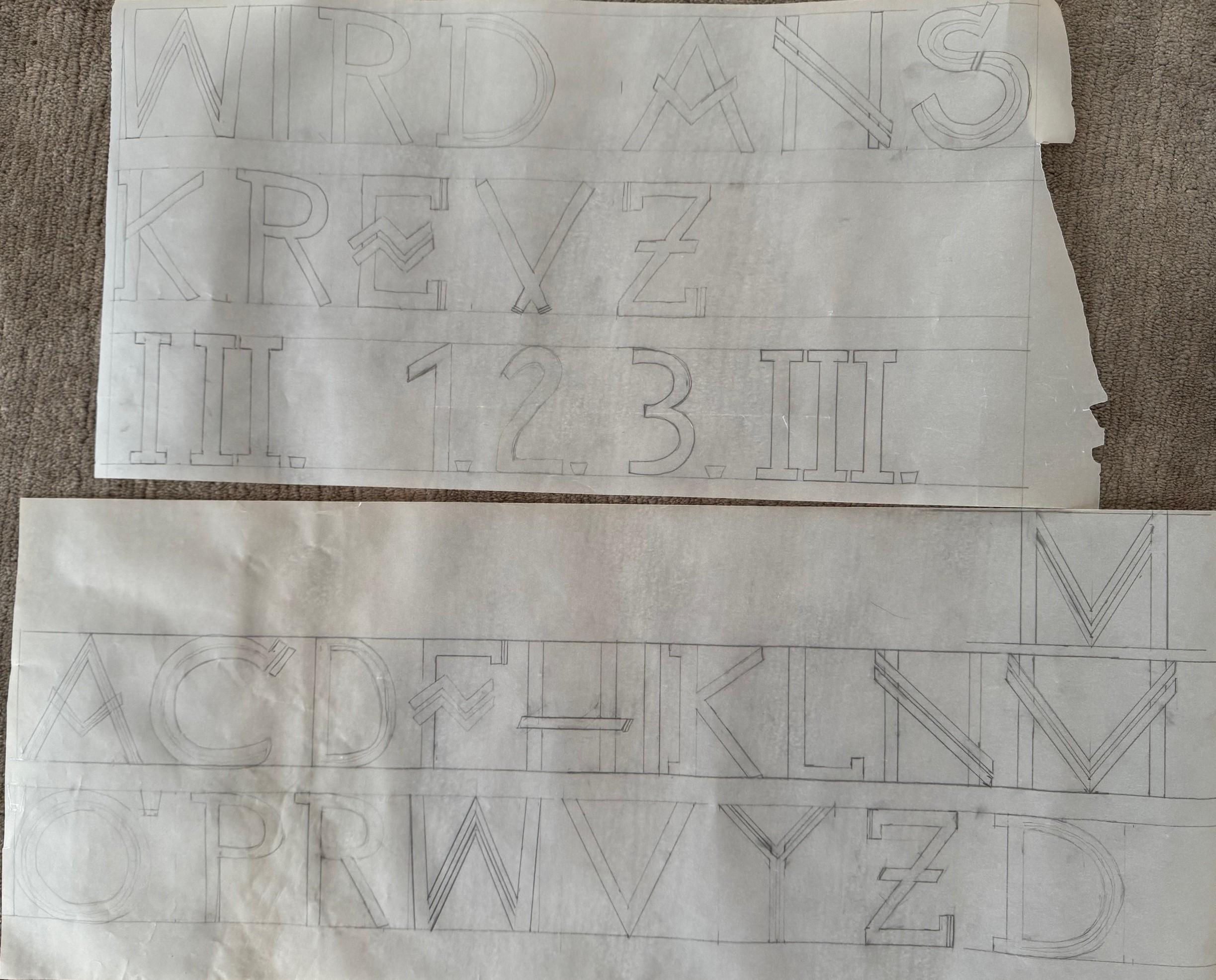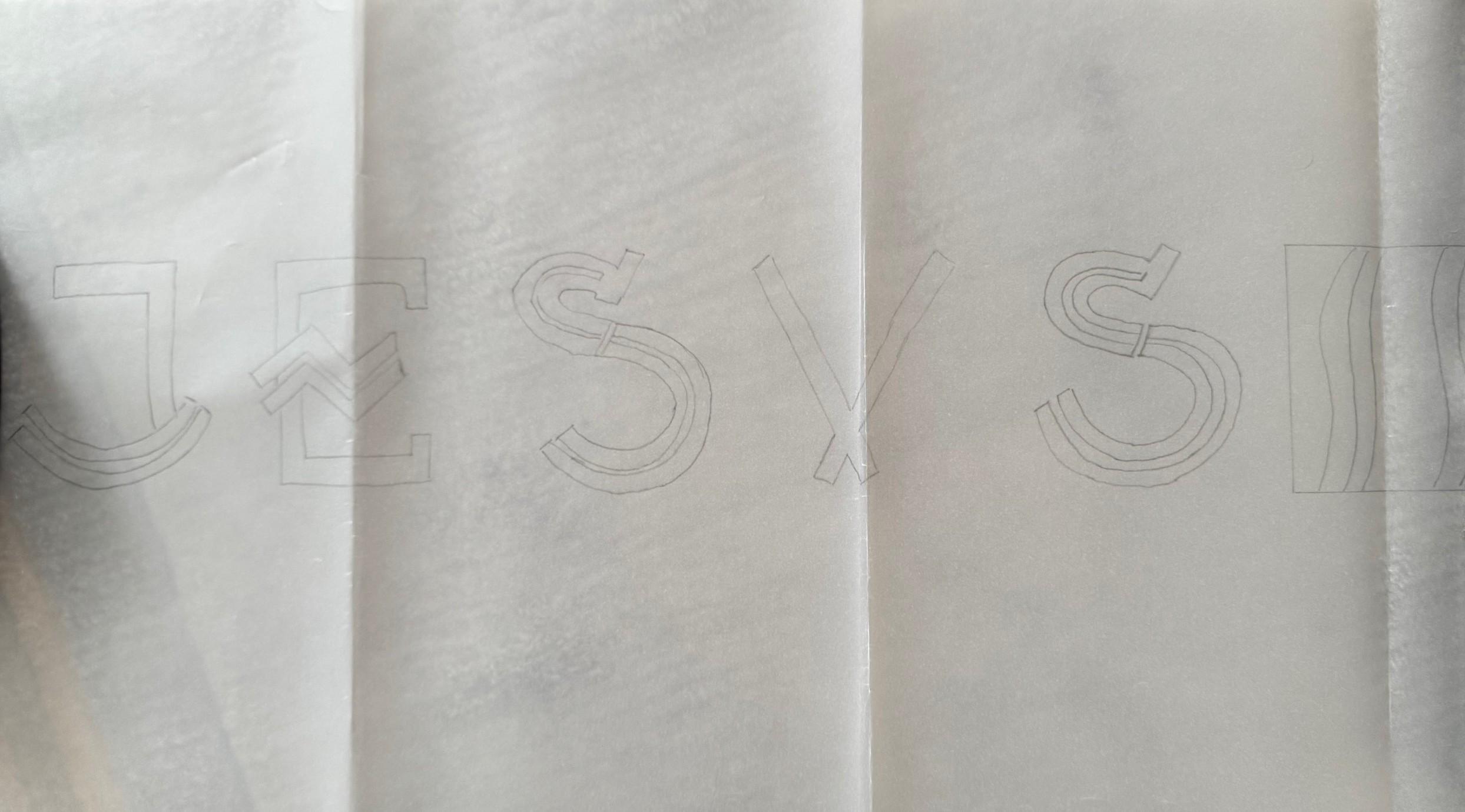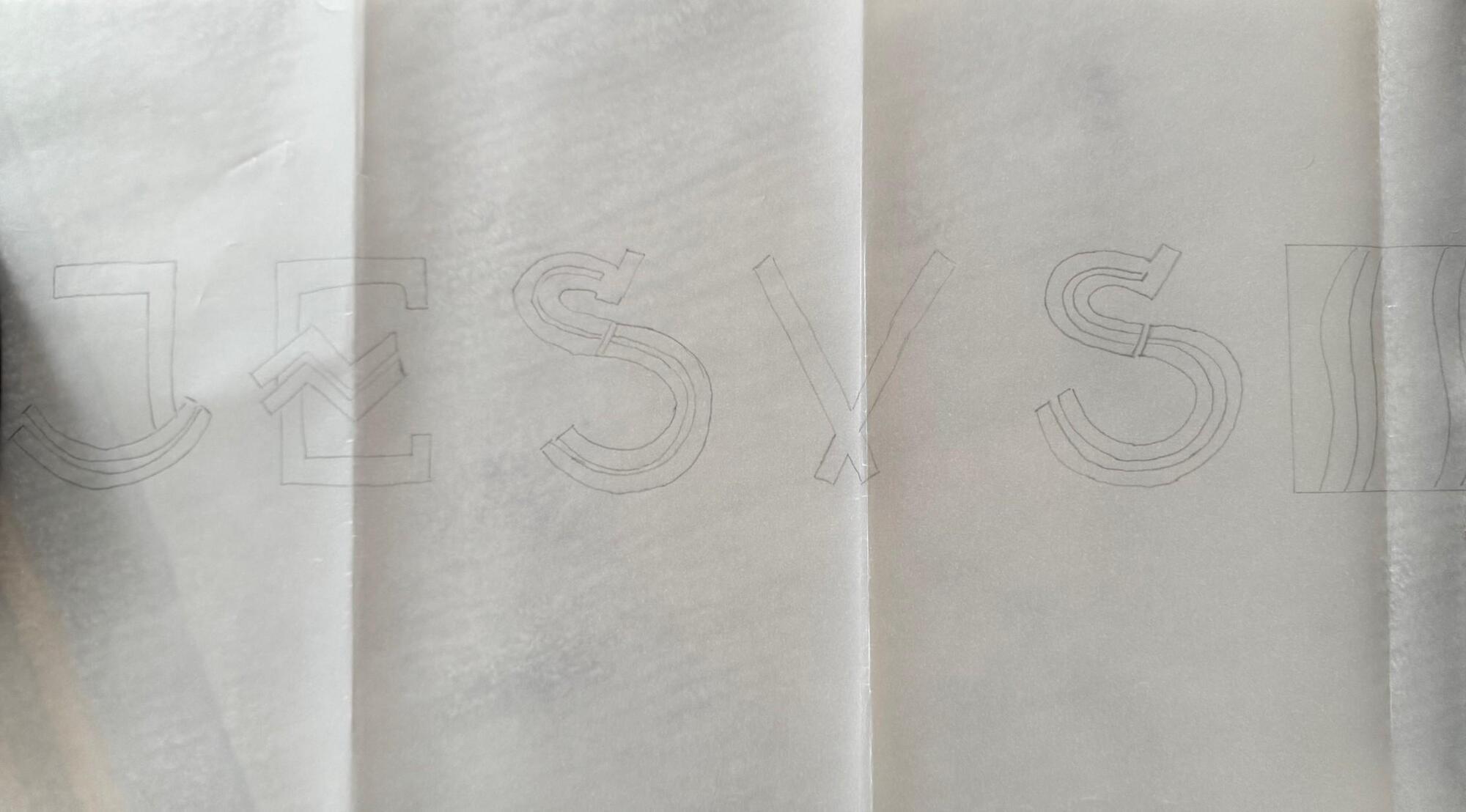
Expressionistische Inschrift
In der Kirche in Dettingen/Main (Architekten: Dominikus Böhm & Martin Weber 1923) gibt es einen expressionistischen Freskenzyklus zum Kreuzweg. Die Inschriften unter den Bildern wurden vom Künstler Reinhold Ewald (1890–1974) selbst gestaltet – in einer eigenen Typographie. Der Restaurator hat aus dem Befund (die Inschriften waren überdeckt und wurden durch eine neobyzantinische Typographie übertüncht) einen komplettes Alphabet erstellt.
Ganz nebenbei wäre das auch ein Beitrag zur Erforschung expressionistischer Epigraphik. Und vielleicht würde auch ein außergewöhnlicher, selbständiger Font daraus.